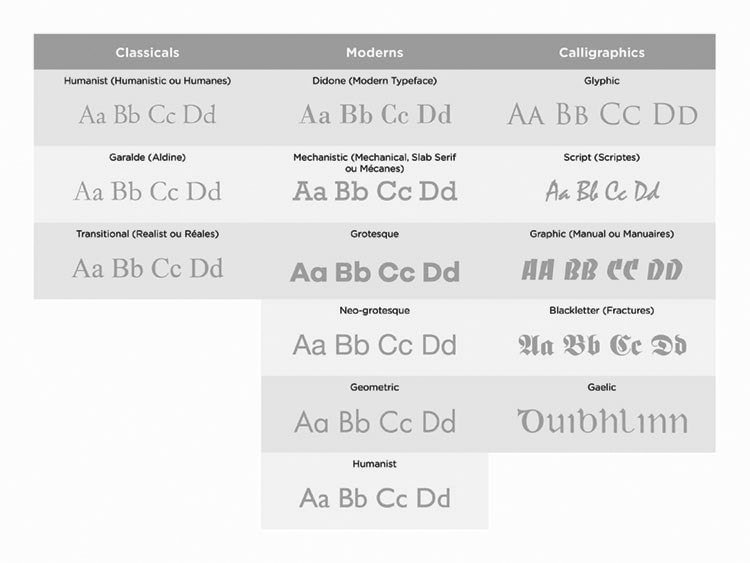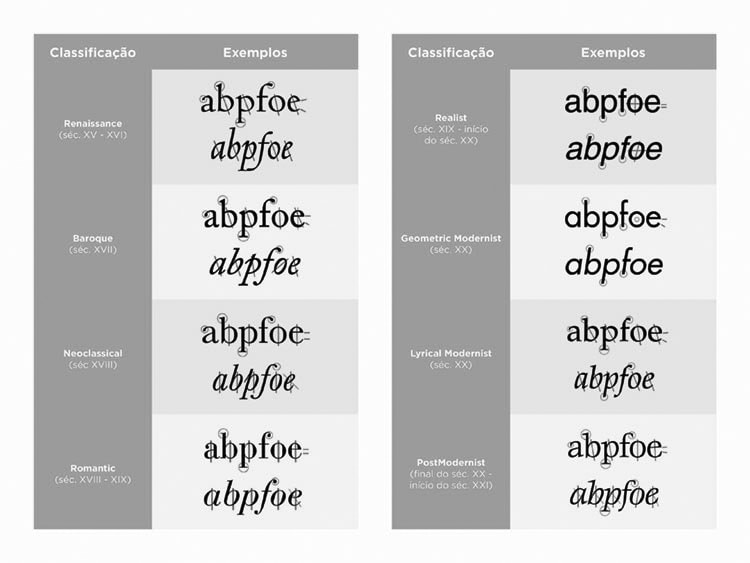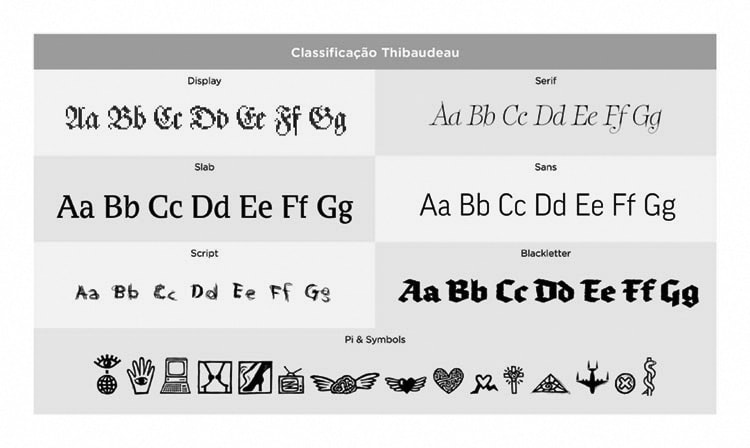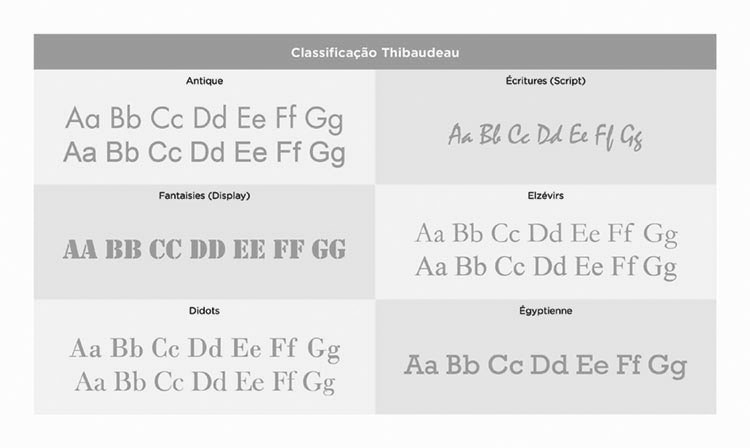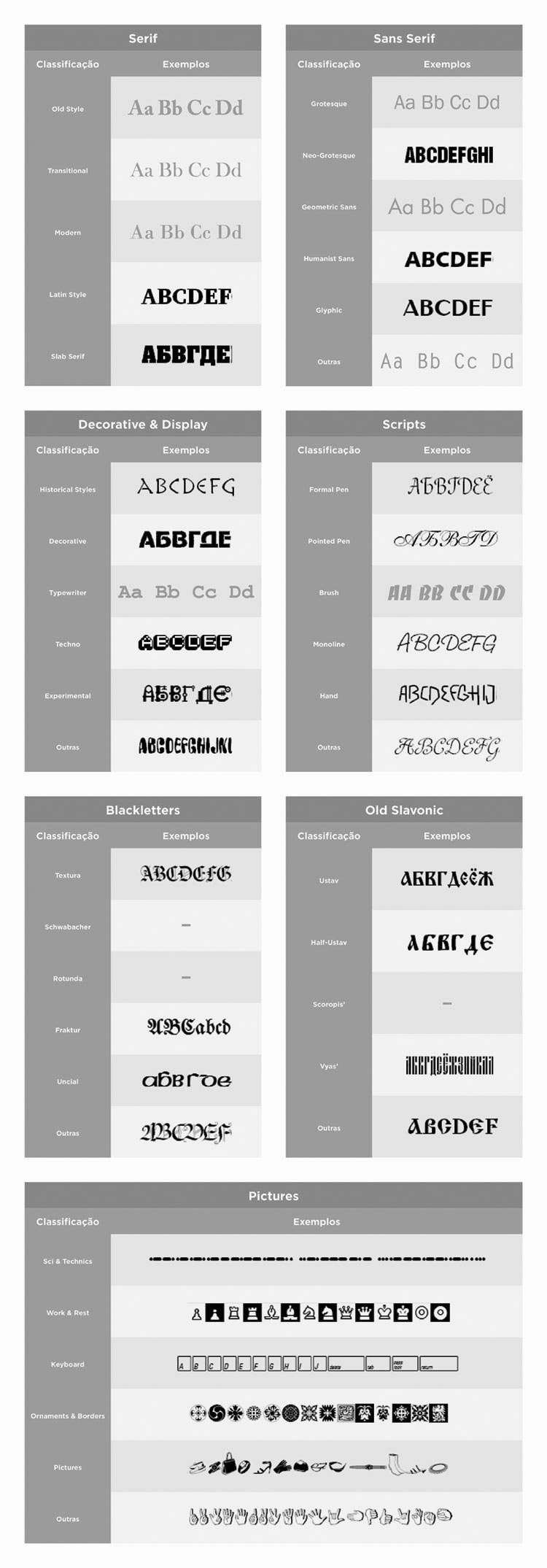
HISTÓRIA DA ESCRITA À TIPOGRAFIA - PARTE 2
Há muito muito tempo atrás, eu publiquei a primeira parte desse artigo (HISTÓRIA DA ESCRITA À TIPOGRAFIA - PARTE 1), foi bem difícil trazer informações com qualidade já que na web existem um zilhão de informações divergentes sobre o mesmo assunto, enfim, sem mais delongas, vamos ao que interessa! :)
OS TIPOS MÓVEIS DE GUTENBERG
Quando aprendemos sobre tipos móveis o primeiro nome que aparece é Johannes Gutenberg (1.398-1.468) como inventor dos tipos móveis, mas o que poucos sabem é que os tipos móveis surgiram muito antes de Gutenberg. Então podemos dizer que ele reinventou os tipos móveis e, consequentemente, revolucionou a indústria gráfica desde então.
Gutenberg contribuiu em vários sentidos para a impressão: processo de produção em massa com tipos móveis, o uso de tinta à base de óleo para impressão de livros, moldes ajustáveis, entre outros. O sistema criado por Gutenberg era economicamente viável tanto para os impressores quanto para os leitores, pois os tipos criados de uma liga de metal (mistura de chumbo, estanho e antimônio) eram extremamente duráveis.
A reinvenção de Gutenberg foi muito importante para o desenvolvimento do Renascentismo (séculos XIV a XVII), Iluminismo (século XVIII) e a Revolução Científica (séculos XVI a XVIII) e lançou os materiais que serviram de base para o conhecimento moderno econômico e a disseminação de conhecimento para as massas.
OS TIPOS ANTES DE GUTENBERG: LESTE DA ÁSIA
Entre 1.041 e 1.048 o chinês Bi Sheng criou os tipos móveis, porém com tipos de argila. O problema foi que os tipos de argila eram muito frágeis e nada práticos para impressões em larga escala, tornando o custo para as impressões muito alto.
Motivado pela invenção de Bi Sheng, o chinês Wang Zhen (1.290-1.333) criou um sistema móvel de impressão com tipos de madeira. A reinvenção de Wang contribuiu para a aceleração do processo de composição com simples dispositivos junto do uso complexo de tipos móveis feitos de madeira. Além desse tipo de impressão utilizando tipos móveis, era também utilizada a técnica de blocos de impressão em madeira (xilografia).
Evidências históricas apontam que os tipos móveis de metal foram criados de forma independente na Coreia, por volta do século XIV. O monge budista Baegun (1.298-1.374) foi creditado pela impressão de um livro importante sobre budismo utilizando tipos móveis de metal.
CLASSIFICAÇÃO DAS FONTES
Ao longo da história foram criadas inúmeras fontes diferentes cada uma focando-se em temas, aplicações, estilos diferentes. Contar como cada estilo surgiu seria algo que levaria muito tempo e talvez não fosse tão interessante quanto contar como alguns profissionais e organizações se preocuparam em classificar cada fonte desenvolvida, então entre um e outro, acabei escolhendo tratar das classificações que surgiram ao longo dos anos.
Existem "n" classificações: de Theodore Low De Vinne, de Thibaudeau, de Daniel Berkeley Updike, Vox System, Vox-A TypI, Schrift Muss Passen, de Geoffrey Dowding, Din 16518N, British Standards System, de Rurari McLean, Lawson's System, entre muitos outros.
O PIIM (Parsons Institute for Information Mapping) organizou um mapa de informação chamado: 25 Systems for Classifying Typography: A Study in Naming Frequency (LINK PARA O PDF): para aqueles que quiserem se aprofundar um pouco mais vale super a pena ler =D, eu achei bem interessante rs
1. CLASSIFICAÇÃO DE THEODORE LOW DE VINNE
Theodore Low De Vinne (1828-1914) fez muito pela melhora nos processos de impressão americanos e também criou um sistema de classificação de fontes, porém as fontes no seu sistema foram classificadas e nomeadas de forma insatisfatória. Ele classificou as fontes da seguinte forma: Display (divididas em Ornamentals, Fat Face, Antique/Clarendon, Blackletter e Script), Romans (divididas em Condensed, Italic, Italian, Moderne e Old Style) e Gothic.
2. CLASSIFICAÇÃO DE FRANCIS THIBAUDEAU
Francis Thibaudeau (1860-1925) foi um tipografo francês, pai do primeiro sistema de classificações dos tipos de letras que batizou de classificação de Thibaudeau. Francis dividiu os diferentes tipos de letras em: Antique, Écritures (Script), Fantaisies (Display), Elzévirs, Didots e Égyptienne.
Sua classificação foi muito lógica e a mais simples, além de feita com uma excelente divisão de tipos e nomenclaturas.
3. CLASSIFICAÇÃO DE MAXIMILIEN VOX / CLASSIFICAÇÃO VOX-A TYPL
Em 1954, Maximilien Vox (seu nome verdadeiro era Samuel William Théodore Monod e viveu entre 1894 e 1974) classificou as fontes em nove classes. Alguns anos mais tarde a Associação Tipográfica Internacional (ATypI) realizou uma adaptação da classificação de Vox e a complementou com mais duas classes de fontes. Essas classes de fontes foram distribuídas em fontes clássicas (humanist, geralde e transitional), modernas (didone, mechanistic, humanist e lineal, a última foi sub-categorizada com os tipos grotesque, neo-grotesque, geometric e humanist) e caligráficas (glyphic, script, graphic, blackletter e gaelic).